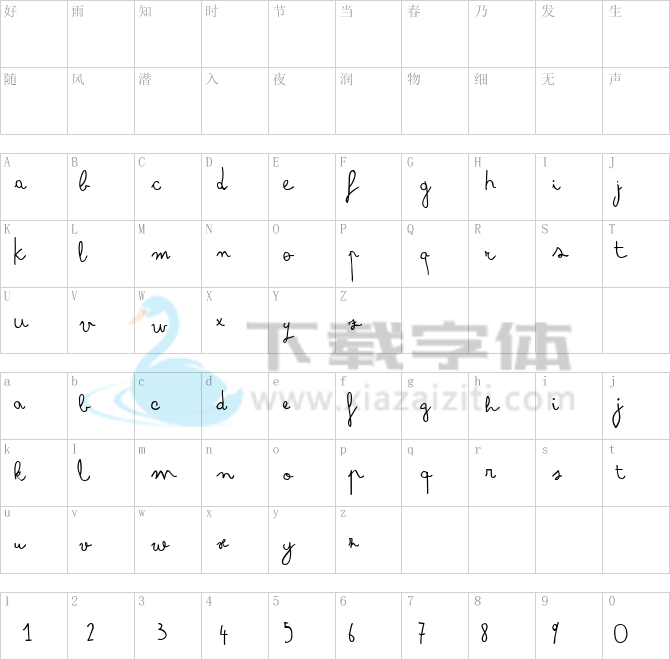
Arsenale White.ttf字体下载,这款字体结构工整、笔画清晰,兼顾美观与易读性,适用于标题、正文、海报、包装、LOGO 等多种场景。字形优雅稳定,风格百搭耐看,适配日常排版与创意设计,让文字呈现更舒适、更具质感。Arsenale White.ttf字体下载一笔一画,皆是细节,以均衡的比例、流畅的线条打造舒适视觉体验,字形端正大气,风格简约现代。无论是商业设计、品牌宣传还是日常排版,都能轻松驾驭,让文字更有格调与力量。Arsenale White.ttf字体下载字体下载。